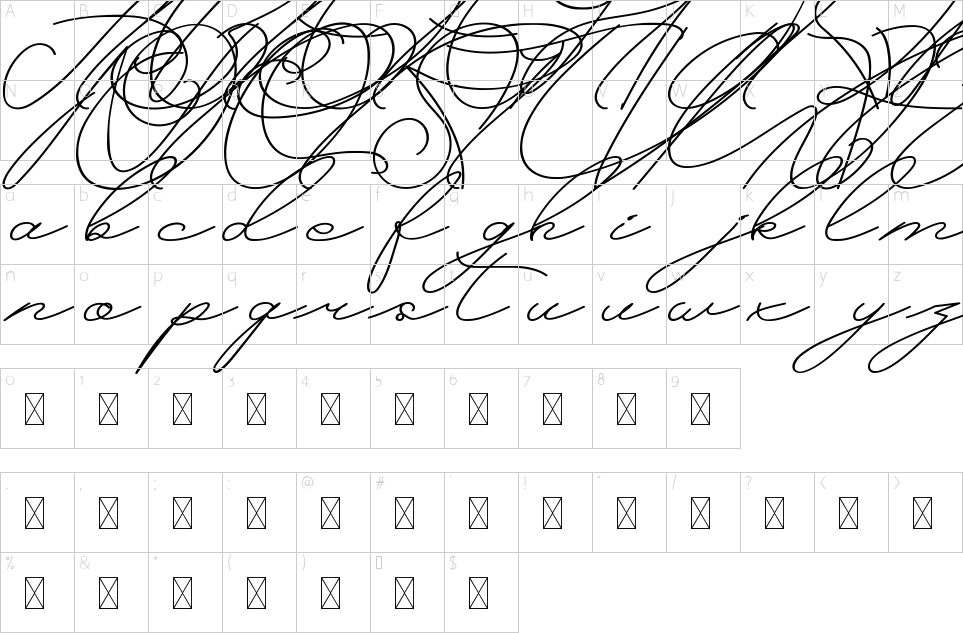
A Butterlies Font é uma opção elegante para designers que buscam uma fonte que combine delicadeza com modernidade. Desenvolvida pelo criador desconhecido CalligraphyFonts, essa fonte gráfica apresenta um design gracioso e versátil que se destaca em projetos de escrita tipo e publicações digitais. Confortável para uso cotidiano, a Butterlies também oferece uma ampla gama de opções de personalização, permitindo que designers adaptem sua aparência conforme suas necessidades específicas. Download da Butterlies Font para Windows e Mac, esta fonte é perfeita tanto para quem busca um visual minimalista quanto para aqueles que valorizam elementos mais decorativos em seus trabalhos digitais. Com uma interface limpa e estilosa, a Butterlies se torna uma escolha segura e confiável para qualquer designer que procura por fontes de qualidade sem custos.